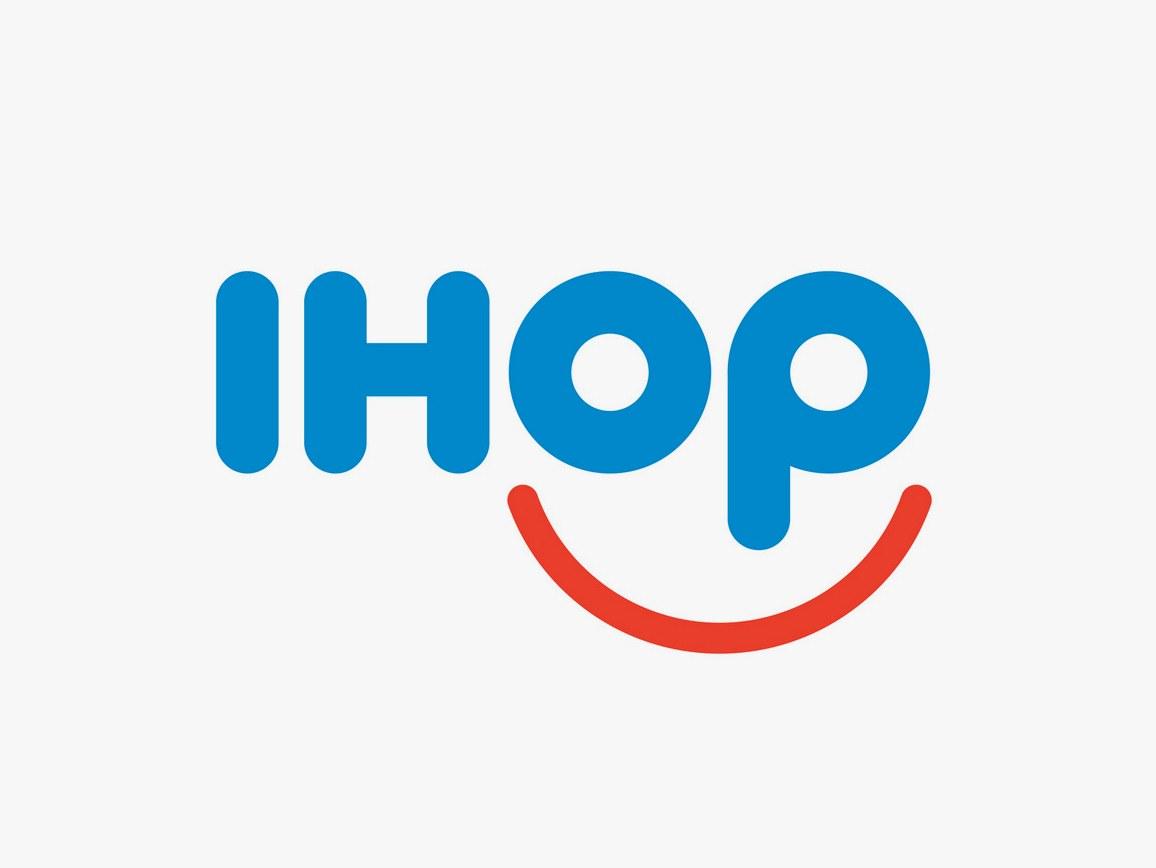
Klein- bzw. Großschreibung in Logos
Ich sitze gerade an einem Logo welches aus vier Buchstaben bzw. einer Abkürzung besteht. Das bisherige Logo ist komplett in Versalien angelegt. Die Lettern geben aus grafischer Sicht leider nicht viel her. Mit Kleinbuchstaben entsteht durch den Wechsel von Ober- und Unterlängen ein deutlich spannenderes Bild.
Ich persönlich mag es eigentlich nicht, wenn Firmennamen klein geschrieben werden. Bei Abkürzungen bin ich etwas unsicher bzw. unentschieden. Allerdings ist das ja durchaus üblich (Siehe dpa, edp, ...). Wie seht ihr das? Spricht etwas grundsätzlich gegen Kleinbuchstaben?
Nö, siehe dpa, edp, … ;-)
Ich denke, es kommt wie immer auf die Umsetzung an. Und halt darauf, ob die Logogestaltung als solche gesehen wird oder ob man daraus (m.E. fälschlicherweise) ableitet, dass der Firmenname auch im Text so geschrieben werden soll. Das ist dann das, das mich oft nervt.
Das nervt in der Tat und diesen Punkt hatte ich bisher auch gar nicht bedacht. :aschehaupt:
Ansonsten sind kleingeschriebene Logos in den letzten Jahren anscheinend schwer in Mode gekommen. Mir fallen da auf Anhieb etliche Redesigns ein. Also nur zu, wenn’s so besser passt …
Übrigens kann auch eine Adhoc-Mischung aus Versalien und Minuskeln funktionieren. Spontan fällt mir da die Restaurantkette IHOP ein. Vielleicht auch eine Überlegung wert …
Während meiner Ausbildung und jetzt auch wieder bin ich in einer Firma gelandet, die sich im Logo klein schreibt. In beiden Fällen ist es so gedacht, dass dies auch im Fließtext durchgezogen werden soll. Persönlich finde ich es komisch, Eigennamen im Text klein zu schreiben und ein bisschen anmaßend, dies mit seinem Design vorschreiben zu wollen. Daher freue ich mich über Kunden, die die Kleinschreibung ignorieren und Firmennamen stattdessen ganz normal schreiben (wie Nachnamen eben, was die Firmennamen in beiden Fällen auch sind). 😄
amazon, adidas, android, zalando, smart … funktioniert doch prima.
smart schreibt sich im Fließtext selbst klein.
Which, to put it mildly, isn’t very smart — especially in English.
In meinem Fall ist es ein Verband dessen Name sich aus mehreren Wörtern zusammensetzt und das Logo besteht aus den vier Anfangsbuchstaben - bisher in Versalien. Ausgeschrieben wird der Name ganz normal gesetzt. Mit amazon oder zalando lässt er sich deshalb nur bedingt vergleichen. Der Fall liegt eher wie bei dpa und da bin ich gerade nicht sicher wie ich das im Fließtext finde. Machen kann man es natürlich...
Also ich verspüre da keinerlei Ambivalenz. Das ist einfach hässlich und doof! :baeh: Ich hätte echt nicht gedacht, dass ein Unternehmen, das ein Unternehmen, dessen Kernkompetenz die Sprache ist, das so durchzieht. Und dann auch noch mit so Sachen wie »dpa Nachrichten« (sic)! Übrigens scheinen englischsprachige Medien den Wunsch der DPA nach Kleinschreibung mehrheitlich zu ignorieren. Die deutschen halten sich meist dran. :-?
Es ist aber nicht die Aufgabe von Fließtext, nicht lahm auszusehen. Mir erschließt sich der Drang, schicke Logoschreibungen regelbrechend im Fließtext einsetzen zu müssen, ohnehin nicht. Dann könnte man auch gleich darauf bestehen, im Fließtext immer auch Schriftart, Strichstärke und Farbe der Marke zu verwenden. Macht auch keiner.
Ich finde gewisse Logoschreibungen auch im Fließtext nett: iPod statt IPod oder Ipod sieht doch irgendwie netter aus. Kann aber natürlich auch an der Wirksamkeit der Apple'schen Marketingstrategie liegen.
Mir ging es bei dem Vergleich nicht um die Schreibweise im Fließtext sondern um die Wirkung im Logo die dann wiederum eine entsprechende Schreibweise im Fließtext nach sich zieht.
Priorität hat für mich erst einmal das Logo. Die Schreibweise im Fließtext ist dann ein untergeordnetes Problem.
Letzteres ist ein zwingend folgendes Problem, also gerade nicht untergeordnet. Es sind zwei Seiten einer Medaille und es muss also direkt mitbedacht werden. Jede vom Rechtschreibstandard abweichende Form (Kleinschreibung, Leerzeichen in Komposita, …) schafft die schon diskutierte Problematik in Fließtexten. Und die ist auch nicht auszuräumen, da allenfalls Standards für eigene Texte aufgestellt und durchgesetzt werden können. Wir hatten dazu ja schon mal eine lange und ziemlich hitzige Diskussion.
für den -sorry- iPod.
Ich glaub in einem Fließtext würd ich z. B.  auch YouTube eher ungebremst verstehen als Youtube.
Doch, natürlich. Genauso wie es die Eltern entschieden haben, ihr Kind Martin zu nennen und nicht Maarten, Morten oder sonstwie, und damit die richtige Schreibweise selbst festgelegt haben.